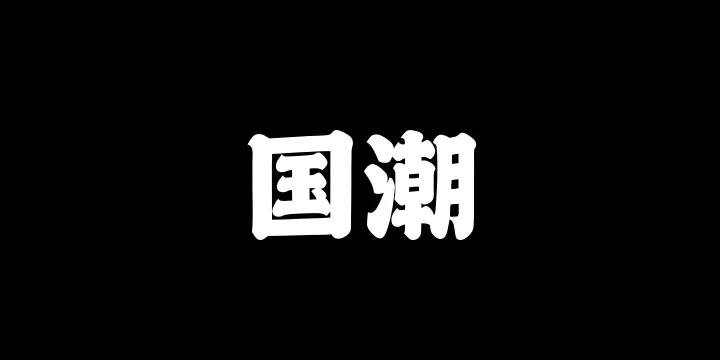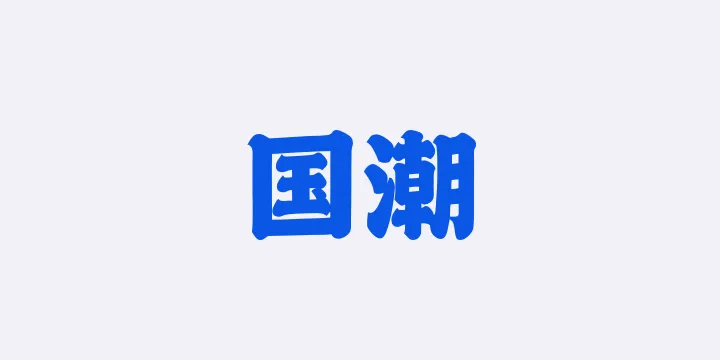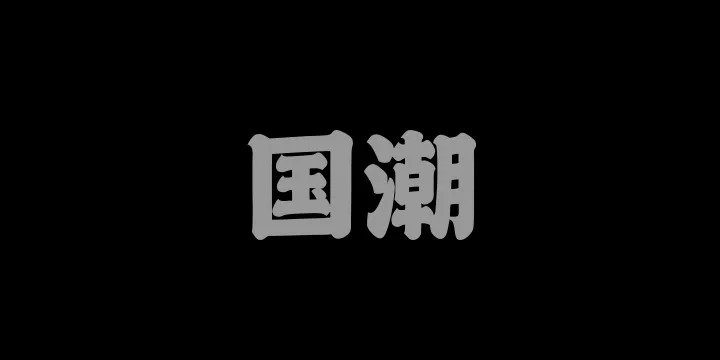
山海国潮 95W By 山海字库 商用字体
字体全名: 山海国潮 95W
字体简介: 山海国潮95W,是一款全新的字体,是山海国潮字体家族系列中的特粗款,编号95W,包含汉字9169个,符号200+个。该字体雄健有力,非常醒目!融入榜书特点,有力、宽厚、方正,如同巍峨的大山,充满了稳重感和设计感。笔画与字形间透露着古雅和刚劲的特点,在古朴的同时而又极富张力,桀骜不驯的特性,霸气外露。它的笔画充满力量感,组合搭配极富强烈的节奏感。在粗细的纵横间,拥有非常规的张力特性。